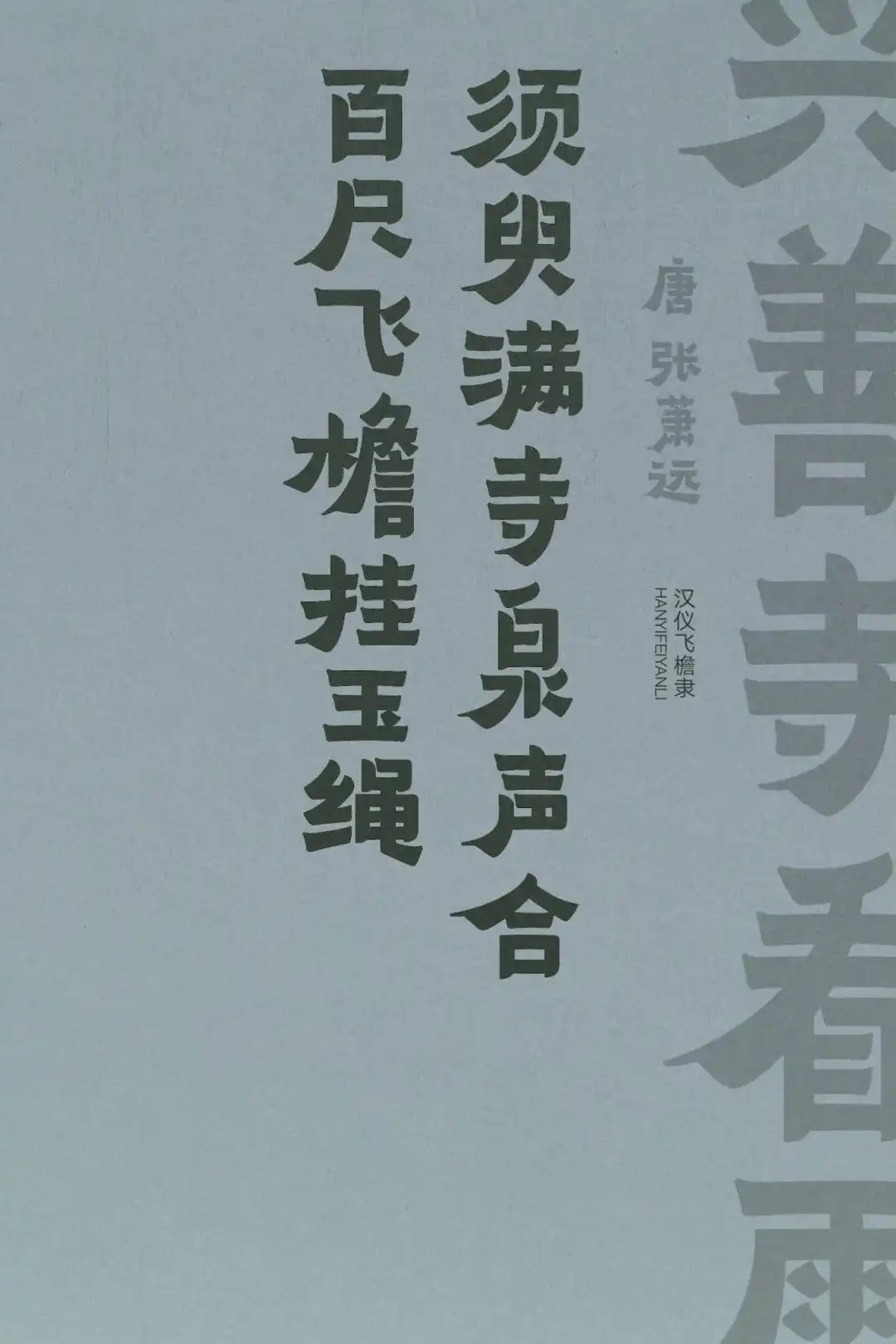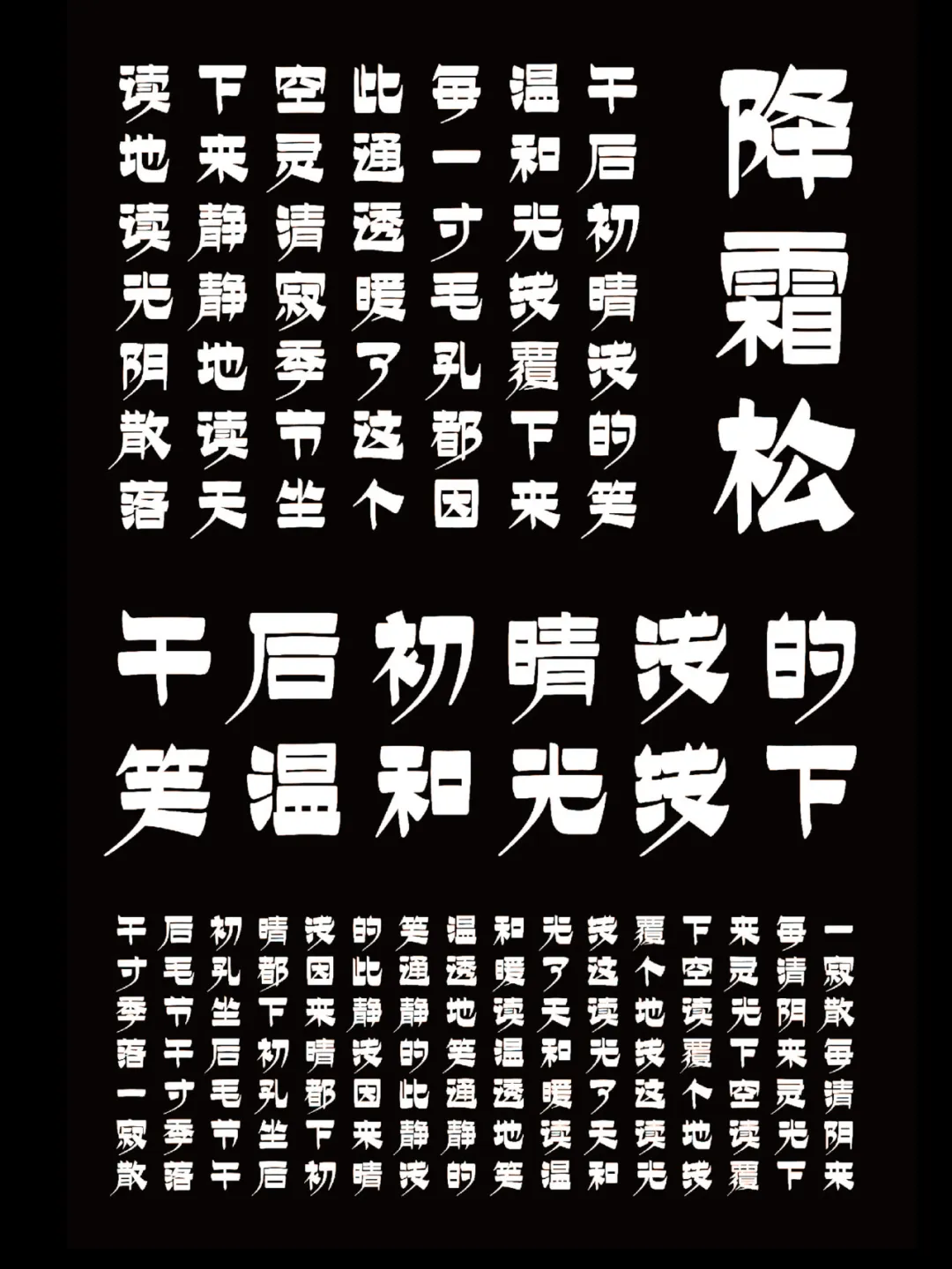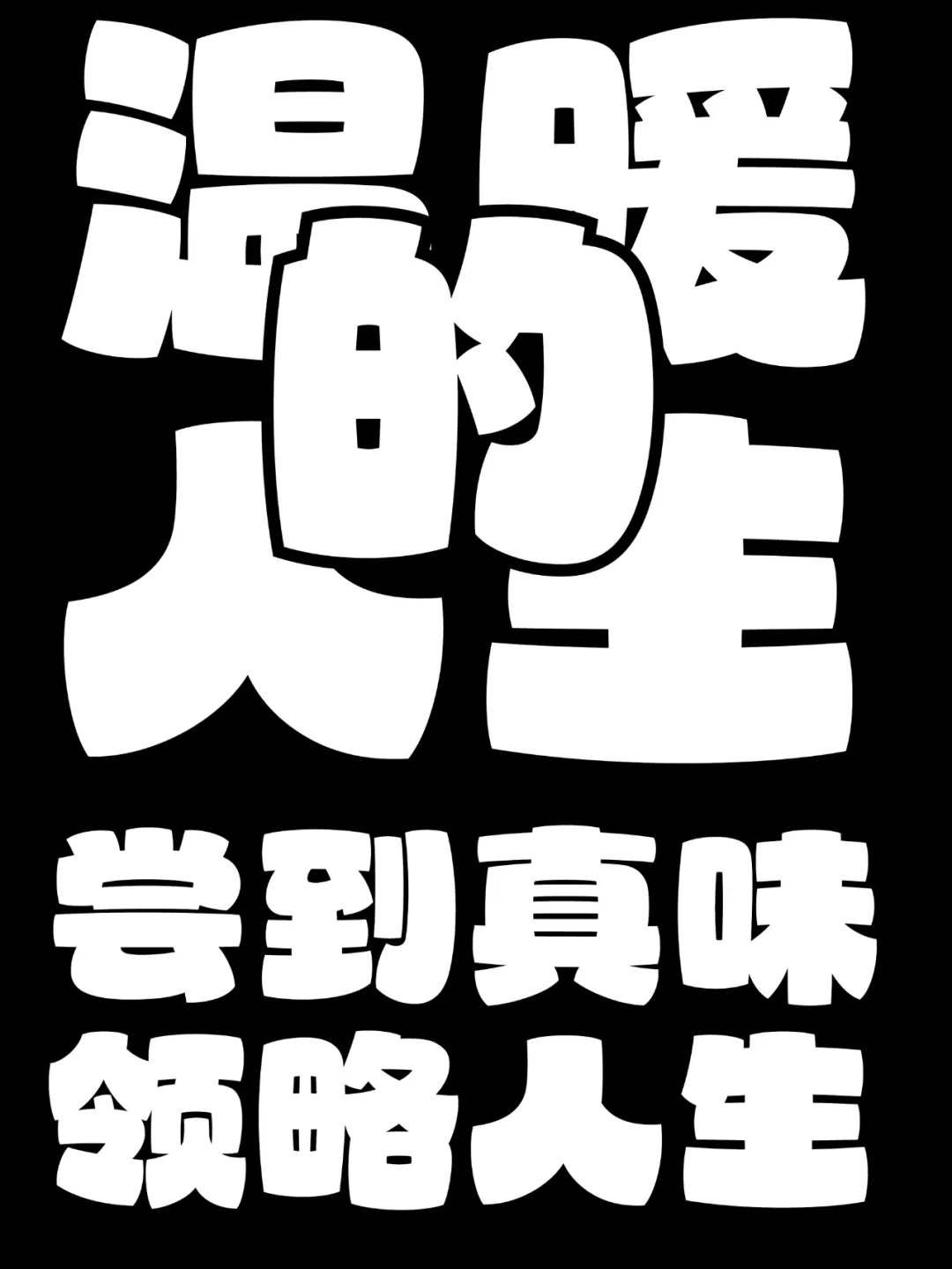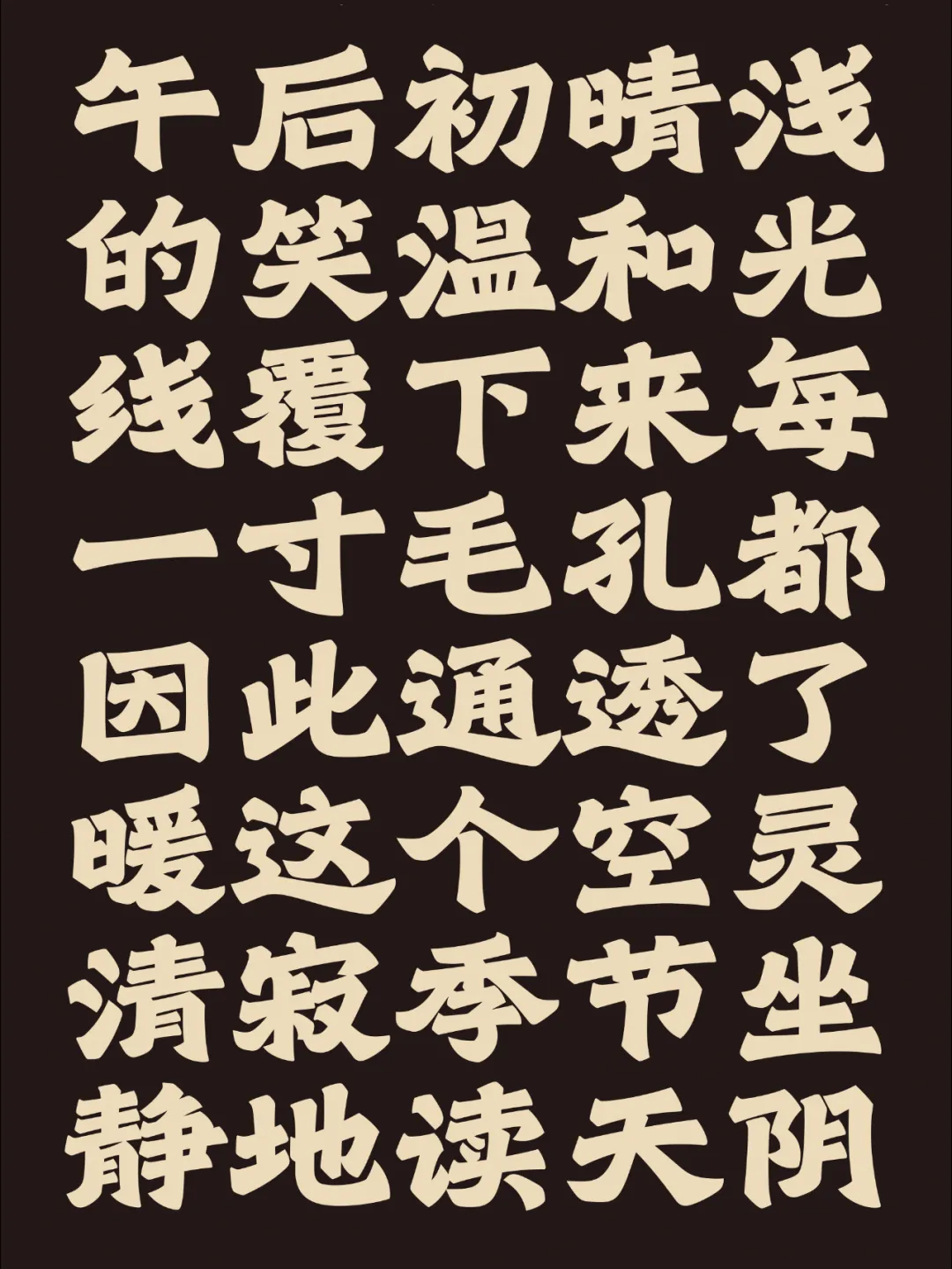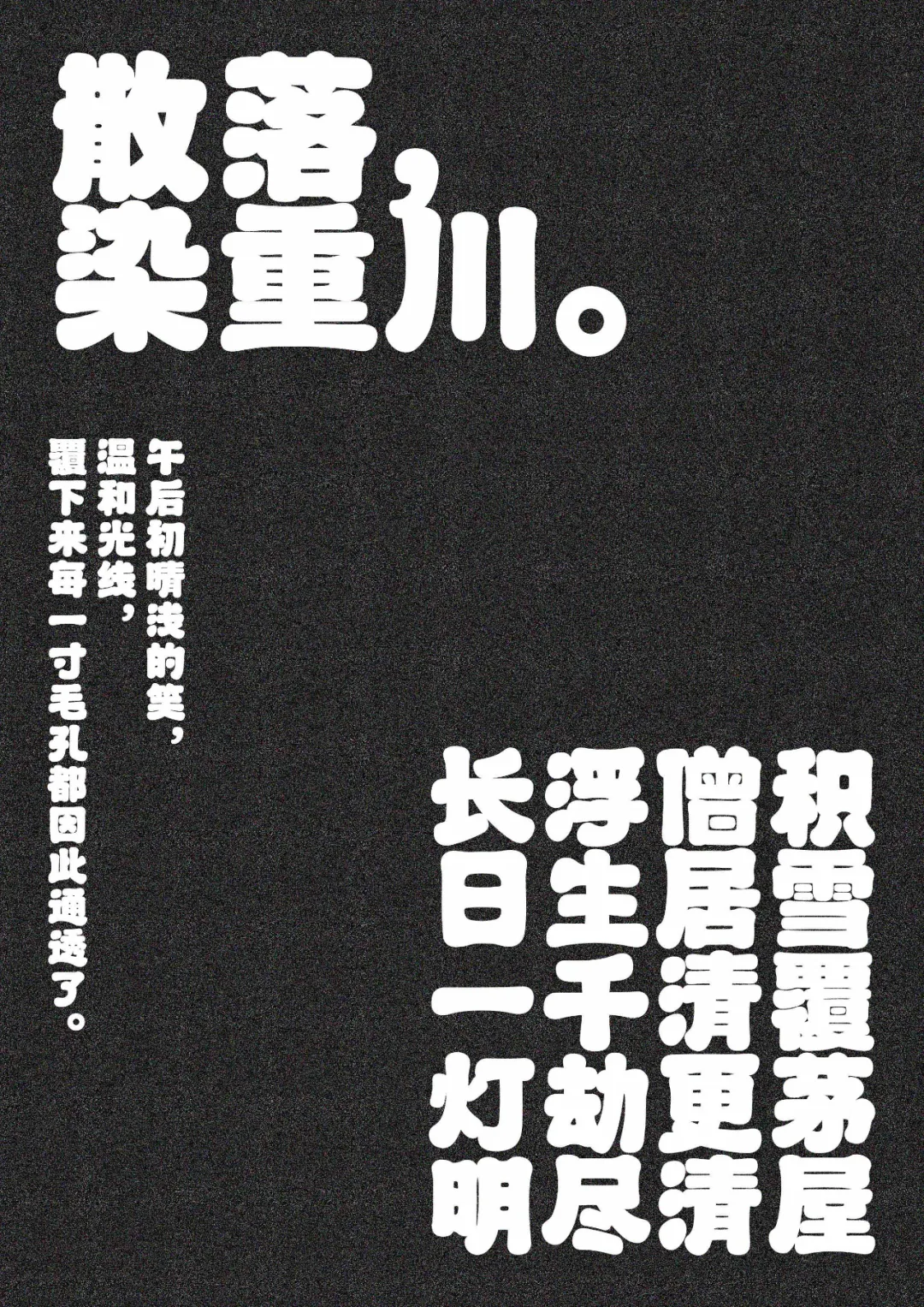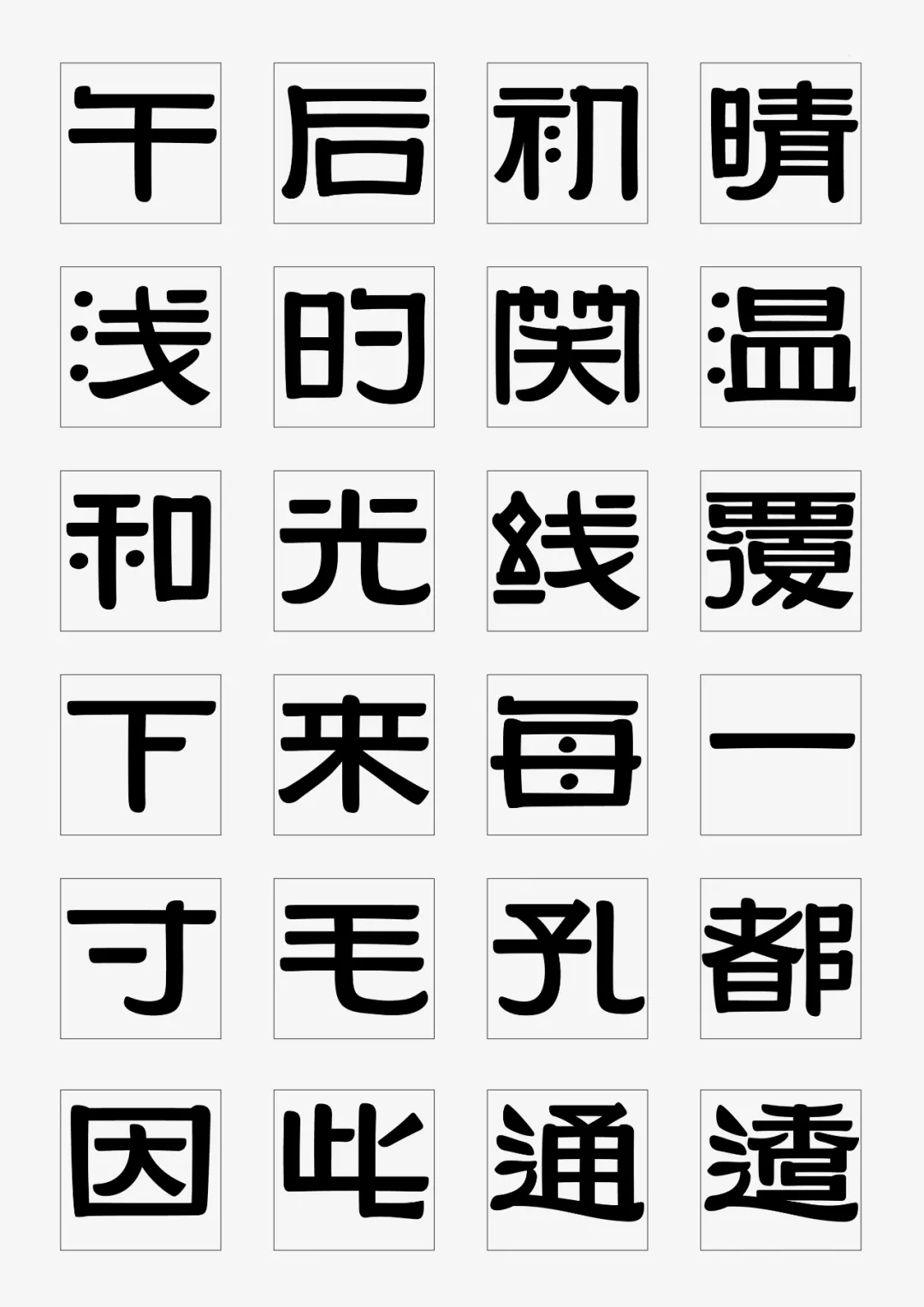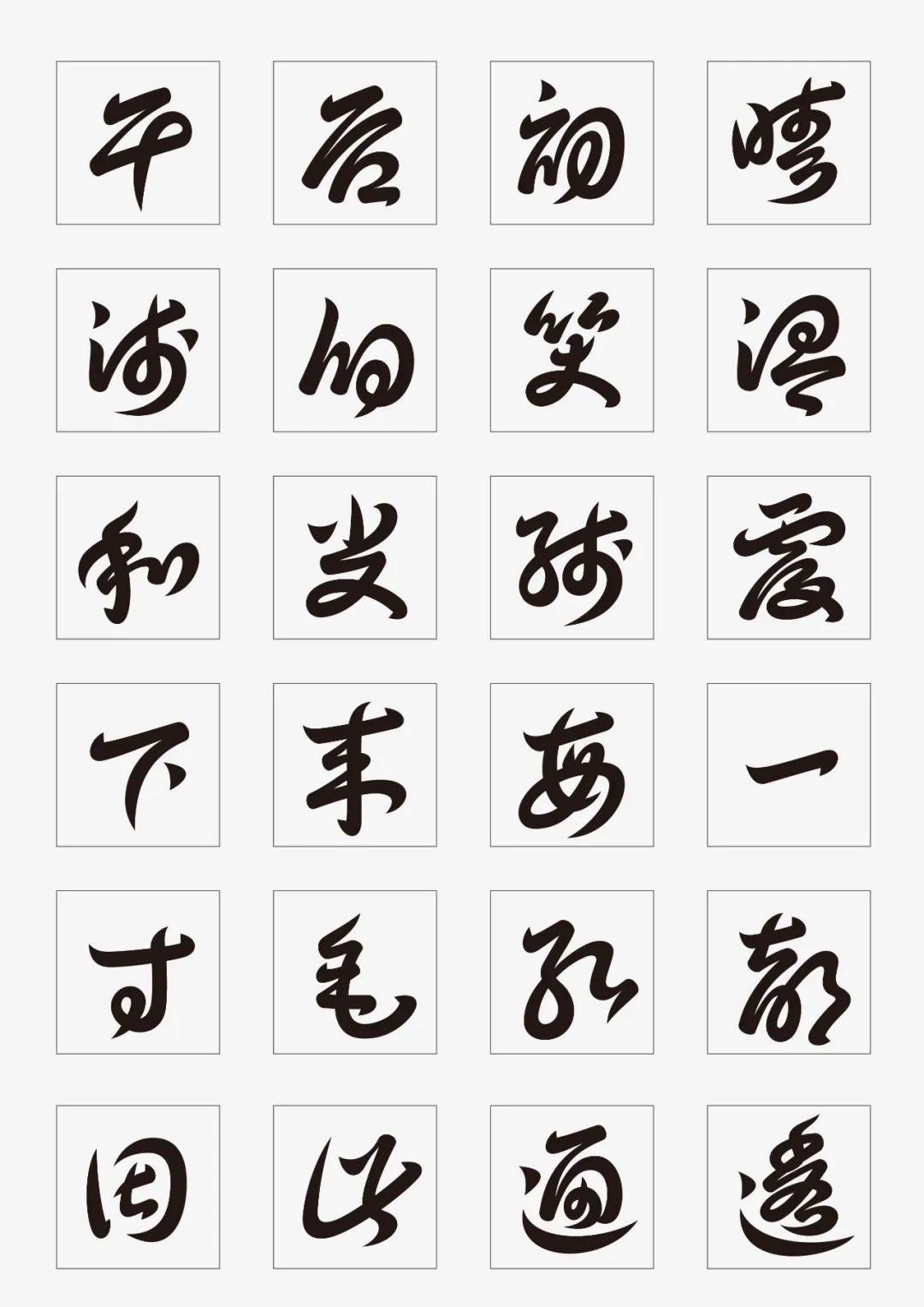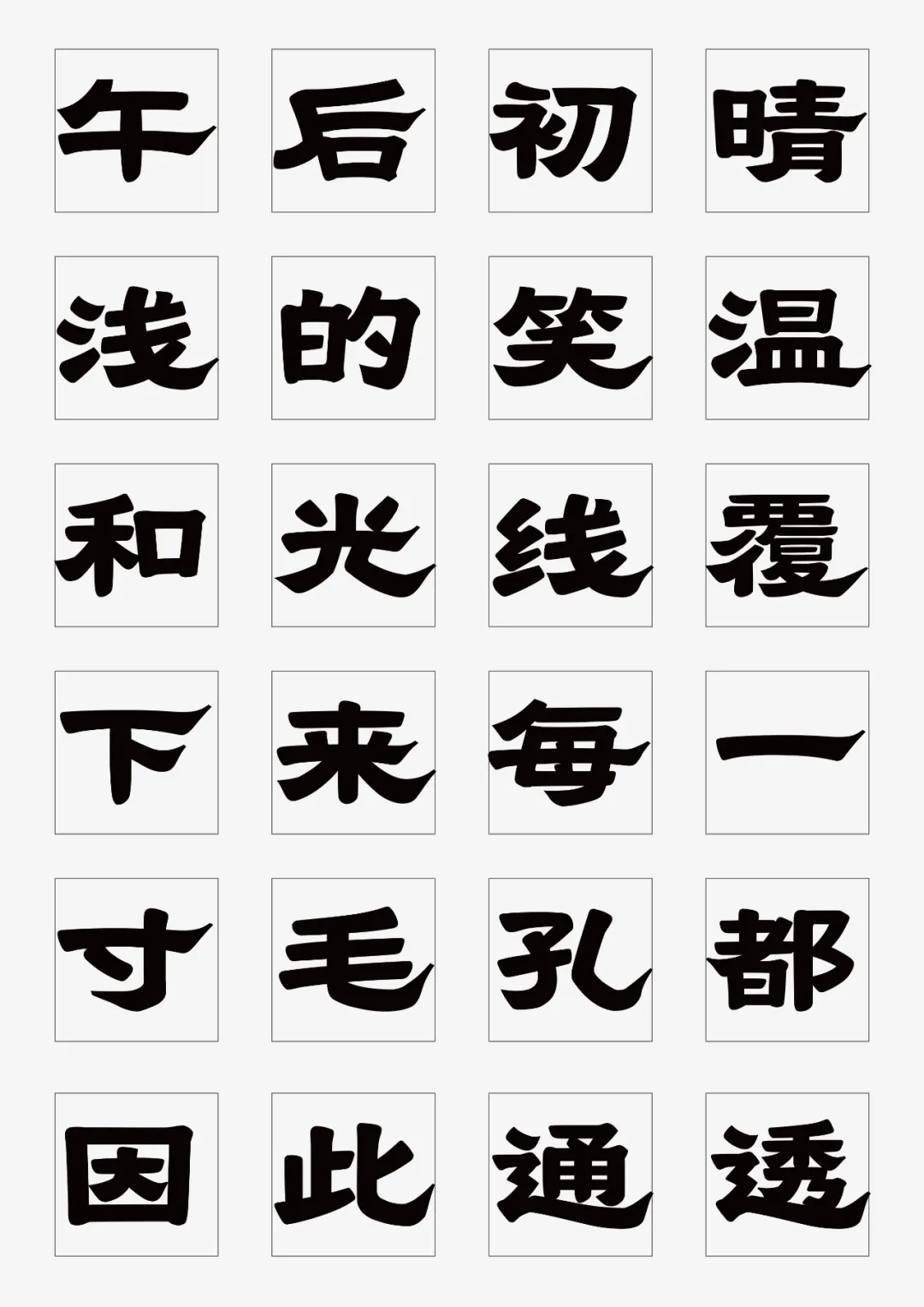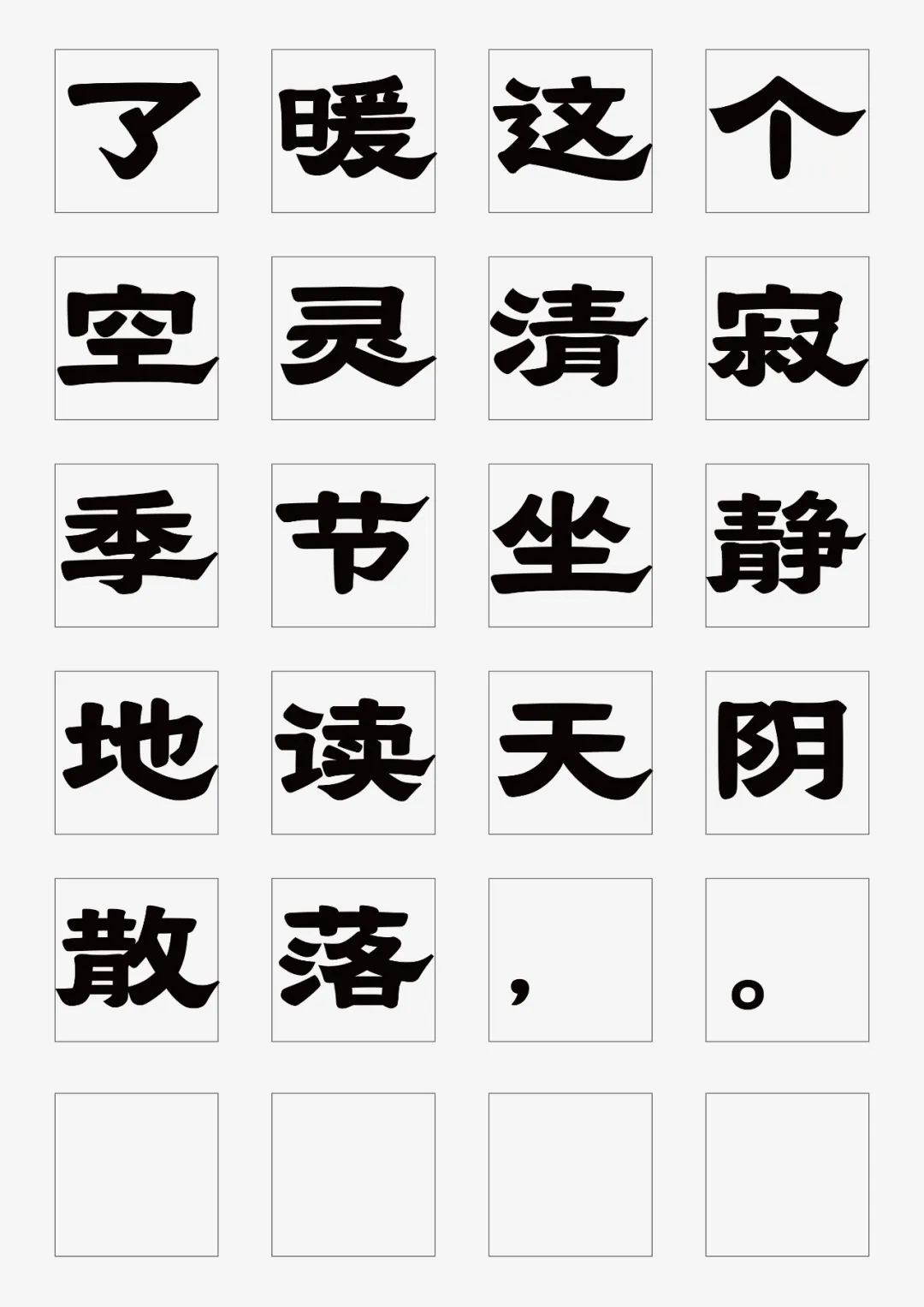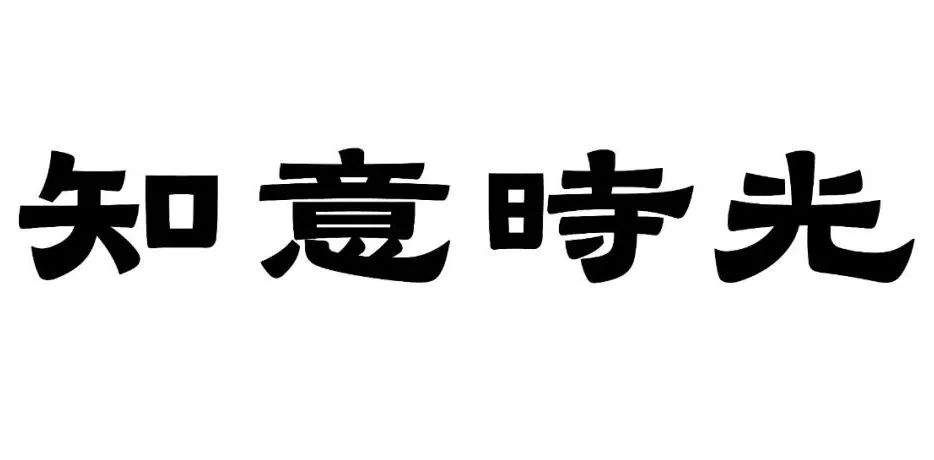
这些优秀的字体作品都出自“一个班”
在视觉传达设计中,字体是构建视觉层次、传达品牌情感与塑造风格的关键,设计师通过字体类型与调整属性,有效引导视觉动线,强化品牌形象。紧跟技术趋势,将创新理念融入字体设计,是提升设计作品竞争力的重要手段。
字体不仅是文字的物理形态,更是情感的载体,能激发观众不同的情感反应,其重要性不言而喻,是每位设计师必须深入掌握的技能。优秀的字体设计确保信息可读性与用户阅读体验,是设计师表达创意、提升作品质量的核心工具。
loyotype自字体精研班开设以来,我们陪跑见证了学员们在国内外设计领域屡获殊荣的佳绩:
趣与业并驱,法与勤相济,则佳作自成,水到渠成矣。
让我们共同领略这些字体的魅力与力量:
Part: A
获奖字体作品
NO.1
《飞檐隶书》
两岸新锐设计竞赛华灿奖 一等奖
第5届字体之星中文学生组 优秀奖
作者 @严谨
《飞檐隶书》从金农隶书作品中提炼,注重古为今用,体势近“漆书”,波磔如飞檐,蕴含简帛古意,创新现代律动,结体左松右紧,笔画方圆结合,从金农书体里学习结构和笔画之外,更汲取了一种勇于开拓的文脉精神。
NO.2
《降霜松》
第40届广东之星设计大赛-学生组-金奖
第23届白金创意国际大学生平面设计大赛-字体设计-银奖
第19届 “中南星奖”设计艺术大赛-银奖
第5届字体之星中文专业组 优秀奖
作者 @夏雯苇
《降霜松体》取法于金农的漆书《童蒙八章卷》,字体既有古代的浑朴钝拙,又有现代简洁大方的气息,撇画清劲潇洒,捺画厚重沉稳,气质上使人联想起霜雪中傲立的松柏;横画粗重而竖画纤细,是一款包含传统基因和现代设计手段的标题属性字体,笔画粗细的强烈对比使这款字体适应海报、包装等多种强调标题属性的应用场景。
NO.3
《扁面黑》
第12届方正奖中文专业组 金奖
作者 @陈和
《扁面黑》是一款个性鲜明的黑体,其字形宽扁,灰度较高成面状,所以取名扁面黑;横竖笔画都略带曲线,起笔留有细微饰角,横竖笔画微微倾斜,整齐中平添一丝灵动,笔画浑厚粗重,中宫放松,字面大,结构饱满;字形风格新颖,刚中带柔,坚实有力,异常醒目。
NO.4
《灯笼黑》
第12届方正奖中文学生组 银奖
作者 @林震
《灯笼黑》的设计灵感来源于闽南、潮汕一代的传统灯笼手写字体,去除传统字体中的饰角,试图传达现代与人文相结合的风格气息。作品模仿球状、柱状灯笼上的视觉展示效果,字重与中宫较大、字面舒展、主笔突出,字型整体较为鼓胀圆润,块状感强,蕴含“团团圆圆”的寓意;字面扁,适合竖排,撇捺较为板直,视觉冲击力强。
NO.5
《大肥》
第12届方正奖中文学生组 铜奖
作者 @孔昊天
《大肥》想要在笔画极粗的情况下表达天真活泼的性格。单纯的粗很难表达出“肥”的概念,所以将字形向四周膨胀,并将结构略微压扁,并将字体下方笔画整体加粗,用略扁的字形,膨胀的笔画和肥厚的下半部分来表现“肥”的感觉。
NO.6
《磐石》
第5届字体之星中文专业组 优秀奖
作者 @龚彬
《磐石》取法于赵之谦隶书法作品,同时结合现代字体设计的设计方法,对书法字体设计进行再创造。通过对赵之谦书法作品常用笔法的形式、结构特征的梳理,提取和分析,再将字形设计为宽扁状,希望字体呈现出如磐石般厚重有力,敦实沉稳的样貌。
NO.7
《染重川》
字体之星中文学生组 评委奖
广东之星设计大赛-学生组-银奖
Award360°年度设计文字
作者 @夏雯苇
《染重川》字体设计笔画圆起圆收,线条柔和而凝练,微有波磔俯仰之势,线条起伏内敛藏巧于拙。笔画厚重如宿墨晕染于纸上,正如草染重川。
NO.8
《清隶简体》
字体之星中文学生组银奖
作者 @李思雯
作品以清代书法家伊秉绶的隶书造型为灵感,保留其古朴敦厚的气质和基本的笔画特征,在此基础上作了由繁体至简体的转化及笔形的统一处理,使其由书法艺术向字库字体转化。
NO.9
《秋光行草》
字体之星中文专业组优秀奖
作者 @Z.z
行草作为介于行书与草书之间的一种书体,其用笔行如流水,大小相兼,险中求平,左右挥酒,力求和谐。这些不仅仅是书体的特点,也是中华文化的特点。他是经过漫长岁月淘洗留下的艺术精髓,是中华民族对人类审美领域的独特贡献。古人云“为君纸尾作行草,烱如嵩洛浮秋光。”我想表达的是秋光行草如同秋日的风光一样美好,就像我们的生活,是收获而不是悲伤,洒脱又稳重。
NO.10
《后动涌隶Bold》
字体之星中文专业组优秀奖
作者 @阿纲
起初是想做一款标题大字类别的字型。取源于老上海的招牌标题字,其中宫的设置灵活巧妙,留下一种“收是为了更好的放”的设定;笔画末端的蓄力感,形似海浪翻涌,涌流不息,通过反复涌动来还原字形特点;在设计过程中参考了榜书的运笔风格,注重浑厚大气的效果。
Part: B
优秀字体作品
@孟旭
@ 龚彬
@ 黄放
@ 叶怡琳
@ 苗阳
@ 孔昊天
作者 @钱浩
作者 @胖老妖
优秀的字体作品不仅是一场视觉大餐,更是一次心灵的触动。这些作品让我们看到了字体设计的无限可能性和创造力。用心去感受、去创造,每个人都能在字体设计领域找到自己的位置和价值。